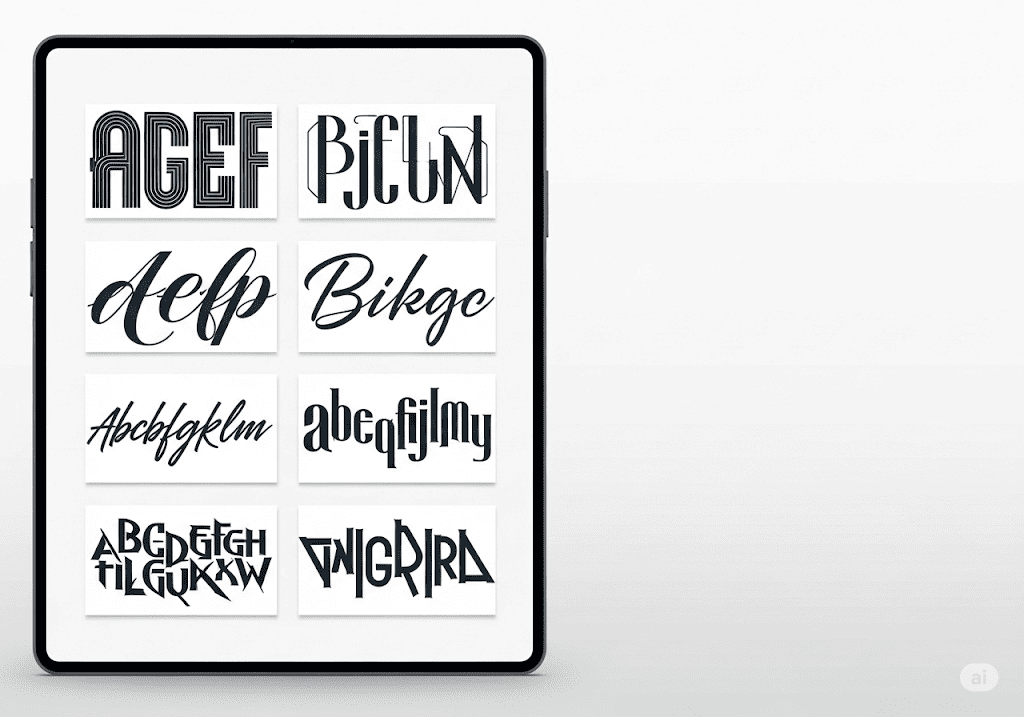
Tải Trọn Bộ Font SVN Việt Hóa Đầy Đủ và An Toàn Nhất
Việc tìm kiếm một bộ font svn chất lượng và an toàn thường rất gian nan, với nhiều rủi ro từ các nguồn không đáng tin cậy. Thực tế, một file font lỗi có thể phá hỏng toàn bộ thiết kế vào phút chót. Bộ sưu tập này không chỉ đầy đủ các font phổ biến như font svn gilroy hay font svn avo, mà còn được chúng tôi kiểm duyệt kỹ lưỡng, đảm bảo an toàn tuyệt đối.
Hãy bắt đầu bằng việc tìm hiểu xem chính xác bộ font này là gì và điều gì làm nên sức hút của nó.
Bộ font SVN là gì và tại sao lại được ưa chuộng?
Tại sao bộ font SVN lại là ‘bảo bối’ không thể thiếu của dân thiết kế Việt?
Về cơ bản, bộ font SVN là một tập hợp các phông chữ quốc tế được chọn lọc và Việt hóa một cách tỉ mỉ bởi STYLEno.1 Fonts (SVN là viết tắt của ‘Style Việt Nam’). Đây không chỉ là một thư viện font thông thường, mà là một giải pháp toàn diện, giải quyết dứt điểm vấn đề lỗi ký tự tiếng Việt (như thiếu dấu, sai vị trí dấu) mà các nhà thiết kế thường xuyên đối mặt, giúp đảm bảo tính chuyên nghiệp cho mọi sản phẩm.
Hãy tưởng tượng bạn đang thiết kế một ấn phẩm quan trọng và dòng tiêu đề “Sáng Tạo Đột Phá” lại hiển thị thành “Sáng T?o D?t Phá”. Lỗi nhỏ này có thể phá hỏng toàn bộ nỗ lực và làm giảm uy tín thương hiệu. Bộ sưu tập này loại bỏ hoàn toàn rủi ro đó, giúp bạn tiết kiệm hàng giờ tìm kiếm và kiểm thử font. Thay vì loay hoay sửa lỗi, bạn có thể tập trung hoàn toàn vào việc nâng cao chất lượng typography và thẩm mỹ cho sản phẩm thiết kế đồ họa của mình.
Khám Phá Trọn Bộ Font SVN Việt Hóa Đầy Đủ từ Tini Tech
Hình ảnh minh họa đa dạng các kiểu font chữ trong bộ sưu tập SVN Việt hóa, từ sans-serif đến script, display
Bộ sưu tập Font SVN Việt Hóa này có những loại nào và ứng dụng ra sao?
Bộ sưu tập font svn full do Tini Tech cung cấp bao gồm hơn 300 phông chữ đã được Việt hóa hoàn chỉnh, đảm bảo tương thích 100% với bộ gõ Unicode. Các font được phân loại khoa học vào các thư mục riêng biệt như Sans-serif, Serif, Script (bao gồm cả các loại font viết tay việt hoá), và Display, giúp bạn tiết kiệm tối đa thời gian tìm kiếm và lựa chọn font cho thiết kế phù hợp với từng mục đích cụ thể.
Để bạn dễ hình dung, đây là một vài ví dụ ứng dụng thực tế:
• Script (Viết tay/Thư pháp): Sử dụng các loại font chữ thư pháp việt hóa như SVN-Dancing Script, SVN-Brush để tạo điểm nhấn cho thiệp mời, logo thương hiệu cá nhân, hoặc các trích dẫn trên mạng xã hội.